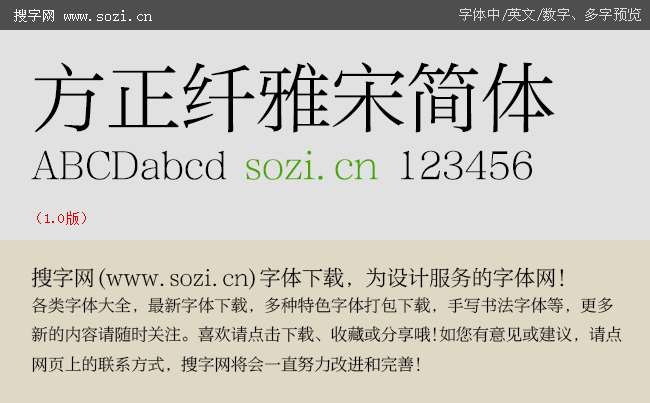
方正纖雅宋簡體(FZXYSJW)
搜字網(wǎng)提供一款方正纖雅宋簡體中文字體下載,方正纖雅宋是一款字形清秀的中文字體,該字體端正大方,纖細(xì)秀美,結(jié)構(gòu)清晰,效果出眾,常用于產(chǎn)品設(shè)計、包裝印刷、報刊雜志、正文標(biāo)題、繪畫創(chuàng)作等廣告設(shè)計場合使用。